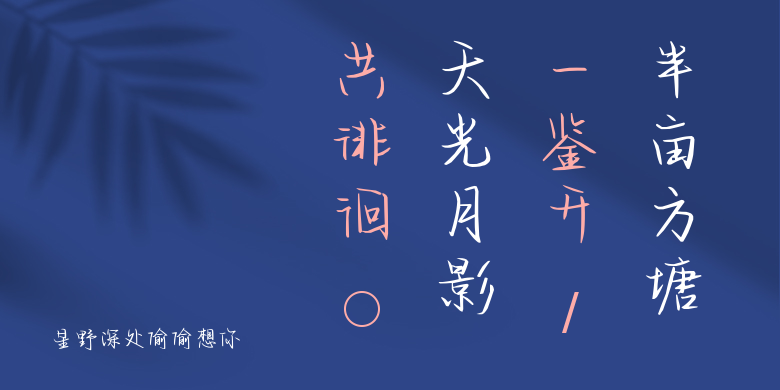
星野深处偷偷想你
星野深处偷偷想你,这款字体结构工整、笔画清晰,兼顾美观与易读性,适用于标题、正文、海报、包装、LOGO 等多种场景。字形优雅稳定,风格百搭耐看,适配日常排版与创意设计,让文字呈现更舒适、更具质感。星野深处偷偷想你一笔一画,皆是细节,以均衡的比例、流畅的线条打造舒适视觉体验,字形端正大气,风格简约现代。无论是商业设计、品牌宣传还是日常排版,都能轻松驾驭,让文字更有格调与力量。星野深处偷偷想你字体下载。